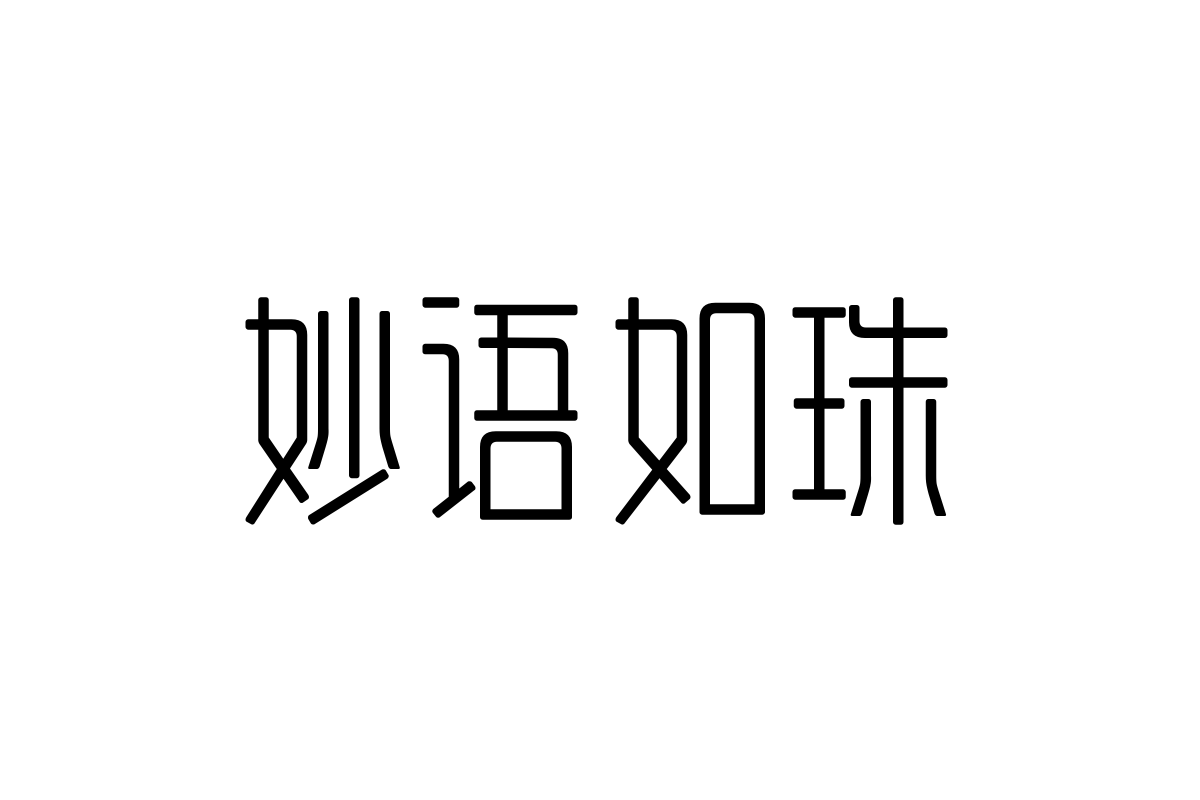
三极雅文体简是一套具有现代感的中文字体,旨在为设计师提供一种简洁、清晰且易于阅读的视觉体验。这款字体的设计灵感来源于传统的书法艺术,但又融入了现代设计元素,使其既保留了传统韵味,又不失时尚感。
三极雅文体简的特点是字形结构紧凑,笔画流畅,线条粗细适中,既适合用于标题和正文,也适用于广告、包装、杂志等各类设计领域。同时,这款字体还具有较强的可读性和辨识度,即使在较小的字号下也能保持清晰可见。
总的来说,三极雅文体简是一款适合多种应用场景的中文字体,无论是用于商业广告、书籍封面还是网页设计,都能展现出其独特的魅力。